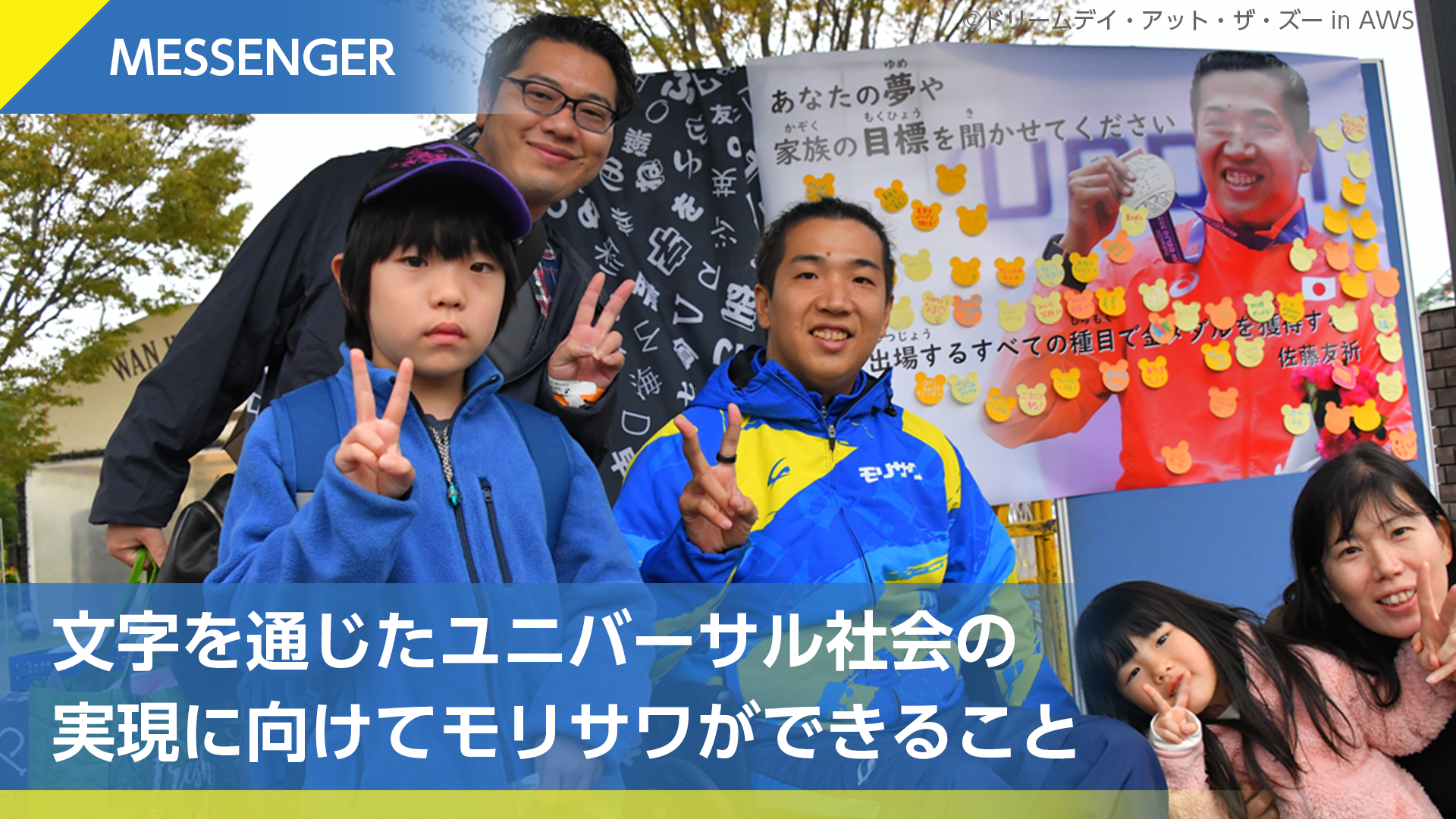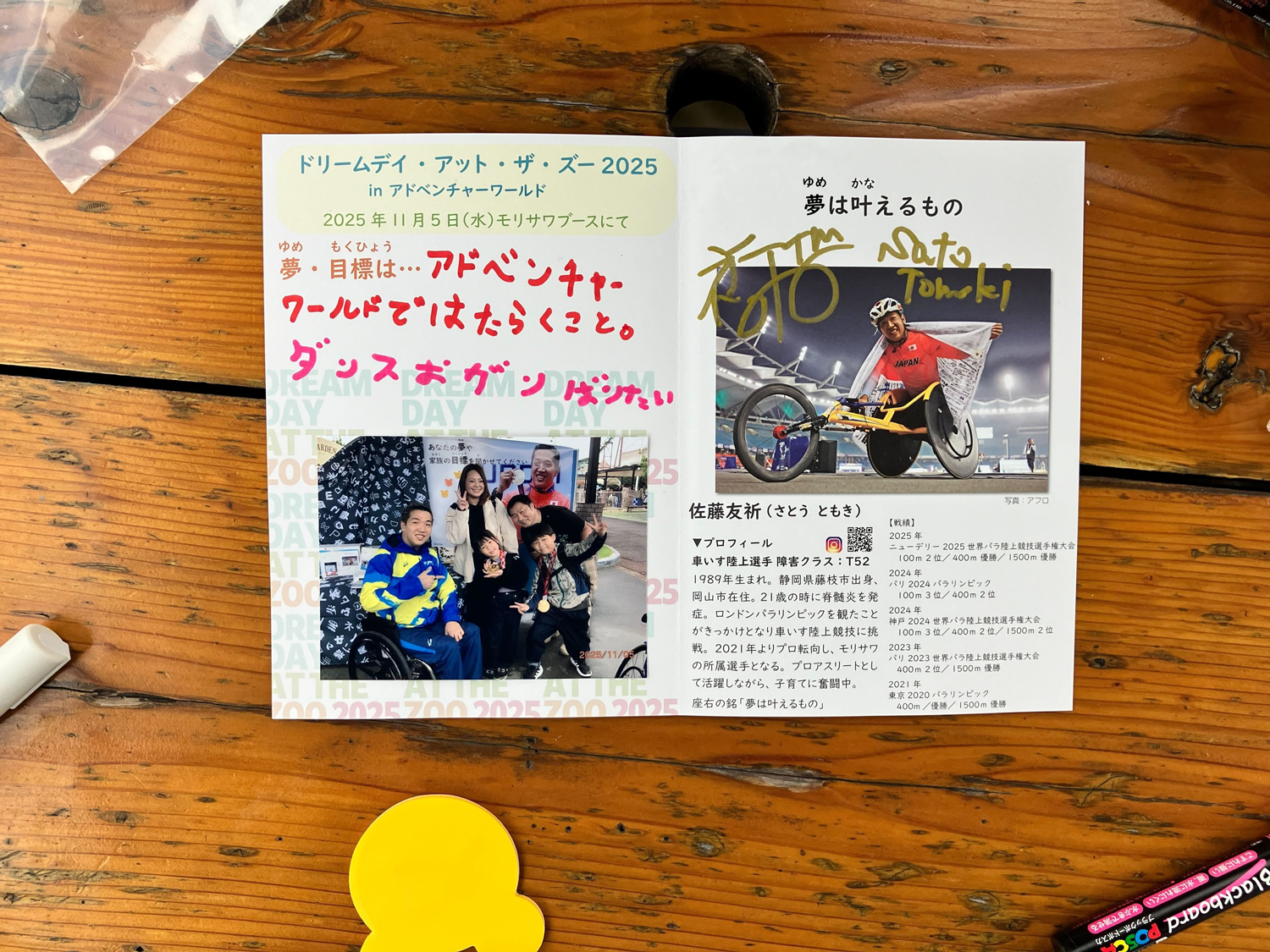
Vol.7 「ドリームデイ・アット・ザ・ズー 2025 in アドベンチャーワールド」レポート
文字を通じたユニバーサル社会の実現に向けてモリサワができること
私たちモリサワは、2025年11月5日(水)に開催された和歌山ドリデイ実行委員会主催の「ドリームデイ・アット・ザ・ズー 2025 in アドベンチャーワールド」(以下、ドリデイ)に2023年から協賛を続けています。3回目となった今回は、初めて企業ブースを出展し、モリサワ所属のパラ陸上選手 佐藤友祈選手とゲストのグリーティングなど新たな企画も行いました。ドリデイとは、全国から18歳以下の障害のある子どもとその家族1,000組・約4,000名がアドベンチャーワールドに1日無料招待されるイベントです。当日は貸切りで営業されるため、障害のある子どもたちやその家族が遊園地や動物園・水族館で、普段は気兼ねしてしまう周囲の目も気にせずに思い切り楽しめます。来場の申し込みはすぐに定員を超え、抽選となる大人気イベントです。
私たちはこのイベントの存在を偶然知り、視覚に困難さのあるゲストが来場した際にもストレスなく過ごすために、フォントが役に立てるのではないかという思いで、担当者にコンタクトをとりました。ドリデイの特設Webサイト、パークガイド、会場内の案内掲示などでは、UDフォント(UD新ゴ、BIZUDゴシック)が採用され、文字の見やすさ、読みやすさにも配慮した環境づくりに貢献しています。
今年の新たな取り組み—企業ブース&佐藤友祈選手との交流
初出展した企業ブースでは、ユニバーサル社会の実現を目指す取り組みの一環として、パラ陸上選手佐藤友祈選手とゲストが、夢や目標を語り合うグリーティングを行いました。金メダリストの佐藤友祈選手とゲストが夢や目標を語り合い、家族全員の思い出となることは、未来に向けた後押しになると考えたからです。ブースでは、東京2020パラリンピックと今年10月の世界選手権で獲得した金メダルをゲストが首にかけて佐藤選手と記念撮影します。撮影した写真をその場で印刷し、この日のための特別なグリーティングカードに貼り、佐藤選手が子どもの名前とご自身のサインを添えてお渡ししました。そこには「夢や目標」を子どもたちが書き込み、未来への思いを表現します。“今日の日の思い出”と“これから”が詰まった、グリーティングカードは特別なギフトとなってたくさんの家族に持ち帰っていただきました。
佐藤選手は、ブースに来てくださったたくさんのゲストの話に耳を傾けながら、ご自身の経験や、自分のペースで夢に向かって進むことの大切さを伝えました。金メダルを手に佐藤選手とお話しする子どもたちや、見守るご家族の目が輝きます。
夢と笑顔が溢れたブース
グリーティングカードのほかにも夢や目標を付箋に書き、佐藤選手が金メダルを持ったポスターに貼っていただく企画も同時に行いました。そこには「ボッチャで金メダルを獲る」「がっこうがんばる」「たくさん笑ってしっかり食べる」など、書かれた目標はさまざま。佐藤選手に会えるのを心待ちにしていたという中学生くらいの兄弟は、車いす陸上にチャレンジしているとして「金メダル」と目標を書き、佐藤選手が持つ金メダルのすぐ横に貼りました。憧れの眼差しで競技のことやトレーニングの方法について、たくさんの質問をします。また、お母さんと相談をしながら、字を書くことが難しい弟さんの代わりに「おねえちゃんとよぶ」と書いてくれたお姉さんの姿も印象的でした。たくさんの子どもたちの力強くも温かな目標が大きな大きなポスターを埋めつくします。
リラックスした穏やかな表情や、全力で弾けるように楽しむ子どもたちの姿はとてもエネルギッシュで、思いがけず私たちスタッフが元気をいただく1日にもなりました。ブースは来場するゲストが途切れることなく終始笑顔で溢れ、またその笑顔が次の笑顔を呼びました。心から楽しんでいるのは障害のある子どもたちだけではなく、一緒に過ごす家族やきょうだい児も同じです。ドリデイに来るゲストみんなの特別な1日が早く当たり前になってほしいと願わずにはいられませんでした。
特別な1日を通じて目指すユニバーサル社会の実現
ドリデイは、外出を控えてしまいがちな障害のある子どもとそのご家族に“安心と自由”を届け、家族や友人と動物園・水族館を思い切り楽しむための“特別な場所”を提供する取り組みです。特性や属性に関わらず一人一人が社会の一員として、ともに助け合って生きていける社会や、違いを認め合えるユニバーサル社会を体験させてくれる機会でもあります。
私たちモリサワは、「フォント」にできることでユニバーサル社会の実現に貢献したいと考えています。例えばUDフォントは、単に“見やすさ”を追求するだけでなく、「より多くの人に配慮する」という思いやりのかたちのひとつです。
ドリデイの理念である「誰もが当たり前に楽しめる社会」は、モリサワが目指すユニバーサル社会と繋がっています。モリサワはこれからもさまざまな企業や団体と協働し、パラスポーツ支援と文字を通じて、ユニバーサル社会の実現に取り組んでまいります。